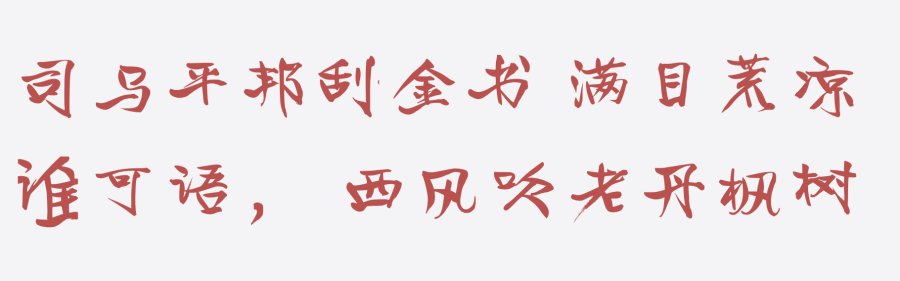
洒脱毛笔手书字体司马平邦刮金书
司马平邦刮金书是一款毛笔字体,横笔画起笔稳重,一波三折,有隶书的风格在里面,撇笔画潇洒犀利,透露出一种洒脱。
司马平邦刮金书
在创作这款字体时,需要保持整体风格的统一性,同时因为会制作成计算机字库,所以在个别字的风格上放弃了词语组合时的个性,为了适配与更多字的组合,不会显得突兀。
司马平邦刮金书